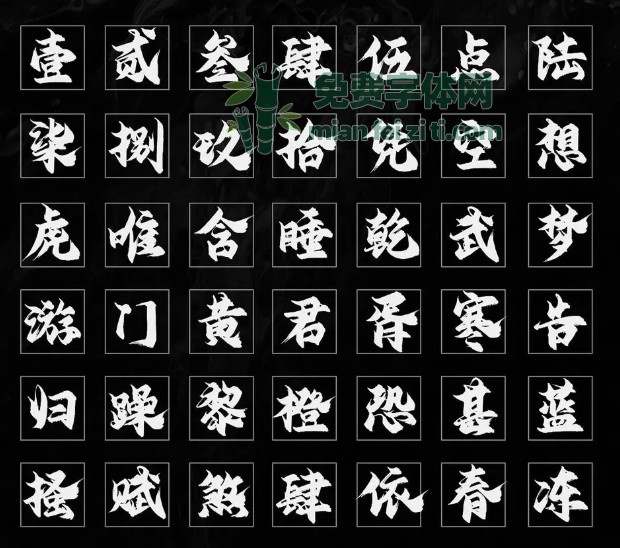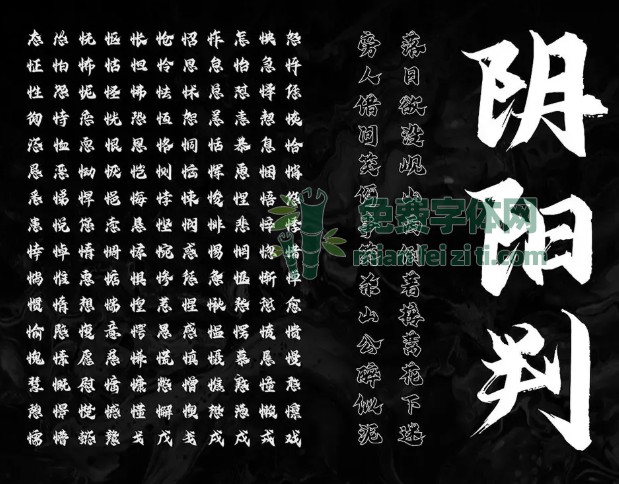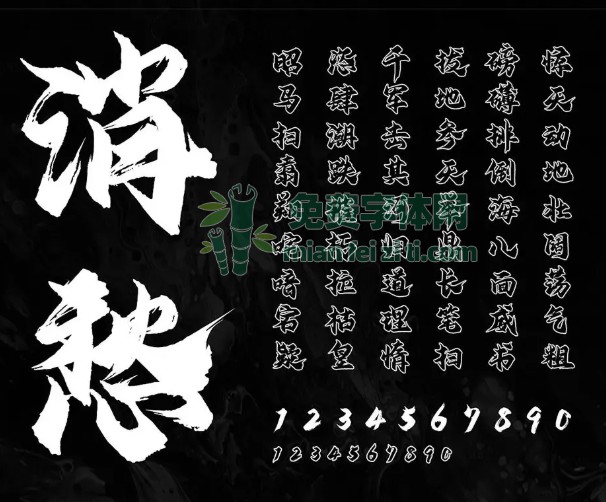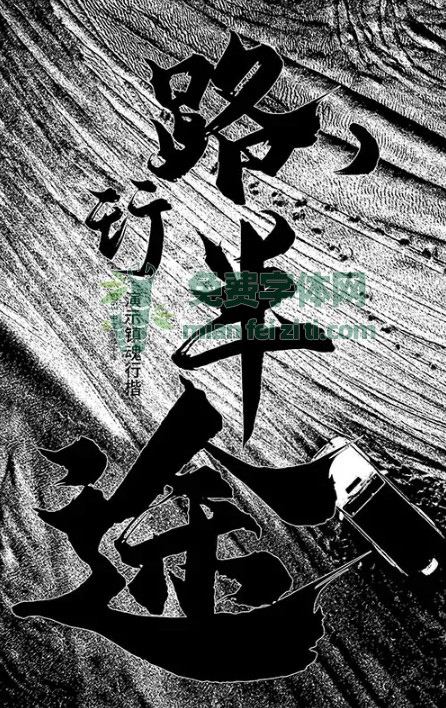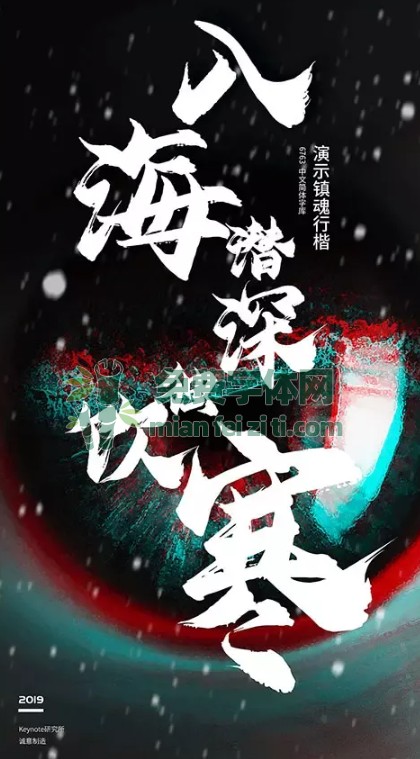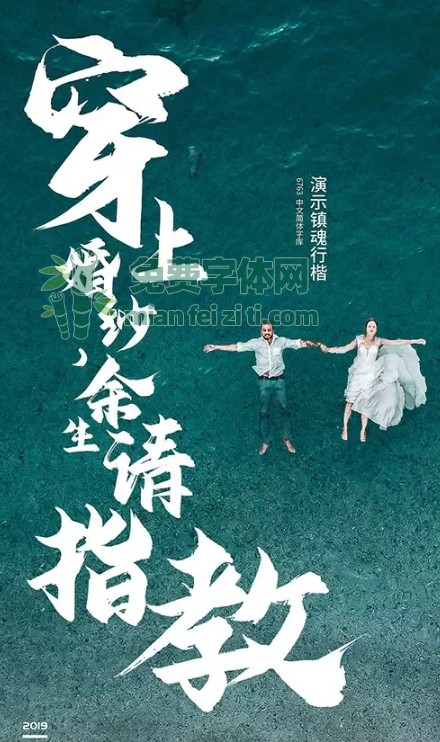
演示镇魂行楷是一款刚劲正气,笔画转折有力的字体,尾部的甩尾有力且丰富的笔触细节体现,给人一种气宇轩昂,方劲威武的感觉。
由于笔画整体厚重粗壮,显得厚重有力,所以非常容易凸显视觉冲击力。但这款字体最大的特色,我觉得还是在于笔触。很多书法体在数字矢量化时难免会失去很多书法细节,导致丢失一些神韵,「书法感」会大打折扣。
人生哥在写这套字体的时候,本身就带有一个目标,希望这套字体能加强笔触气势。
书法字体虽然一定会必不可少地丢失笔触,但他做了很多努力,反复写、改、调,最大化的保留细节,所以「演示镇魂行楷」的笔触细节非常感人。
所以,如果对于笔触要求不算特别高,这个字体不加笔触几乎都可以直接用: